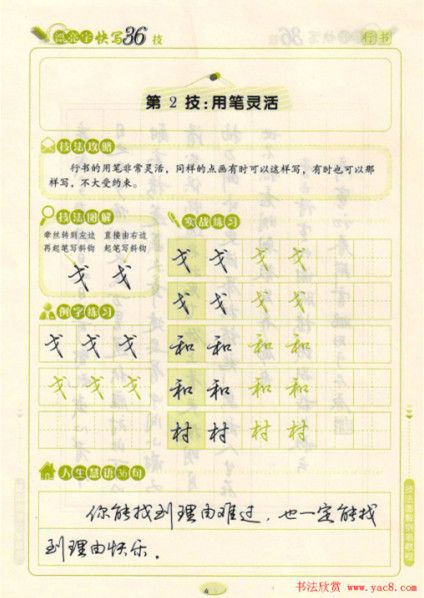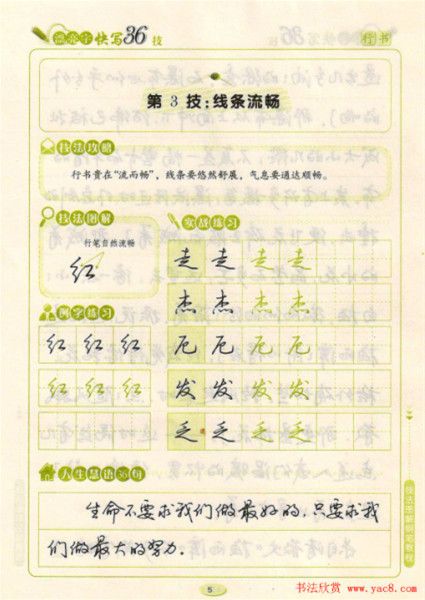
荆霄鹏行书《漂亮字快写36技》钢笔行书练字帖下载(共37张)
荆霄鹏,中国硬笔书协会员、其硬笔书法作品在全国各类大赛中获奖近百次,出版硬笔书法字帖四十多种,深受广大书法爱好者及学生的好评。《墨点字帖·技法图解钢笔练字教程:漂亮字快写36技》是技法图解行书钢笔练字教程之一,主要特色:①技法攻略:言简意赅,轻松把握练字要点;②技法图解:形象易懂,突破枯燥文字讲解;③实战练习:举一反三,拓展延伸巩固强化;④人生慧语:寓教于乐,一语中的点击人生。是一款非常适合成年人、大学生进行练习的练字字帖模板。
本练字字帖模板目录如下所示:
①正确的握笔姿势与执笔方法
②漂亮字快些36技
第1技:牵丝萦带
第2技:用笔灵活
第3技:线条流畅
第4技:轻重得宜
第5技:以圆代方
第6技:以简代繁
第7技:以收代放
第8技:以点代捺
第9技:偏旁多变
第10技:笔顺多变
第11技:体态多变
第12技:疏密得体
第13技:收放有致
第14技:顾盼生姿
第15技:俯仰向背
第l6技:高低错落
第17技:适当夸张
第l8技:左辅附右
第l9技:右辅附左
第20技:连横化板
第21技:诸横收放
第22技:穿插合理
第23技:横笔等距
第24技:竖笔等距
第25技:繁者慎之
第26技:联撇参差
第27技:天覆伸展
第28技:地载收敛
第29技:小字勿大
第30技:大字勿小
第31技:长字勿扁
第32技:扁字勿长
第33技:纵腕有力
第34技:斜字有力
第35技:中宫收紧
第36技:巧借草字
③练字作品欣赏